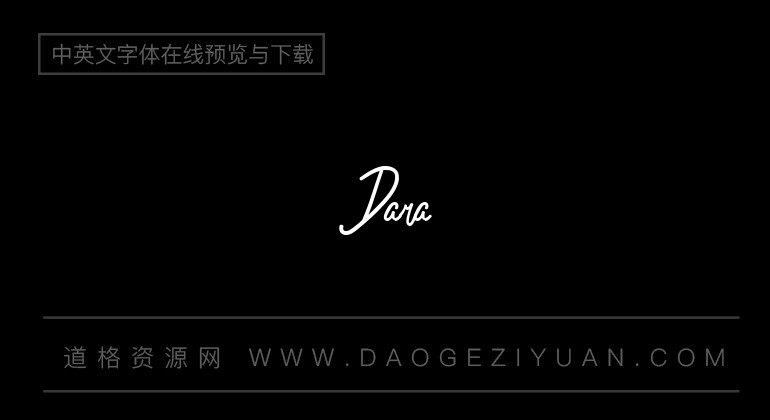
Dara
Dara 是一款简洁、清新的英文字体,它的特点是细节刻画精细,笔画线条优雅,具有较强的视觉冲击力,可以有效地提升设计的质量。Dara 字体的字形特点是字体的笔画纤细,笔画均匀,笔画之间的间距也较为合理,使得字体具有良好的可读性,可以用于多种类型的文本,如标题、报刊文字等,也可以用于广告、网页等设计中。
Dara是一款非常不错的手写艺术字体,具有很好的视觉感,适合于文化类的宣传设计、商业类品牌的广告和产品包装设计以及个性化文字排版等较多场景。